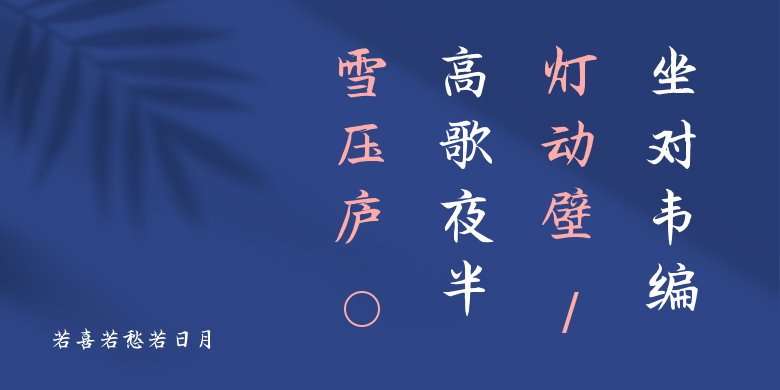
若喜若愁若日月
若喜若愁若日月,这款字体结构工整、笔画清晰,兼顾美观与易读性,适用于标题、正文、海报、包装、LOGO 等多种场景。字形优雅稳定,风格百搭耐看,适配日常排版与创意设计,让文字呈现更舒适、更具质感。若喜若愁若日月一笔一画,皆是细节,以均衡的比例、流畅的线条打造舒适视觉体验,字形端正大气,风格简约现代。无论是商业设计、品牌宣传还是日常排版,都能轻松驾驭,让文字更有格调与力量。若喜若愁若日月字体下载。